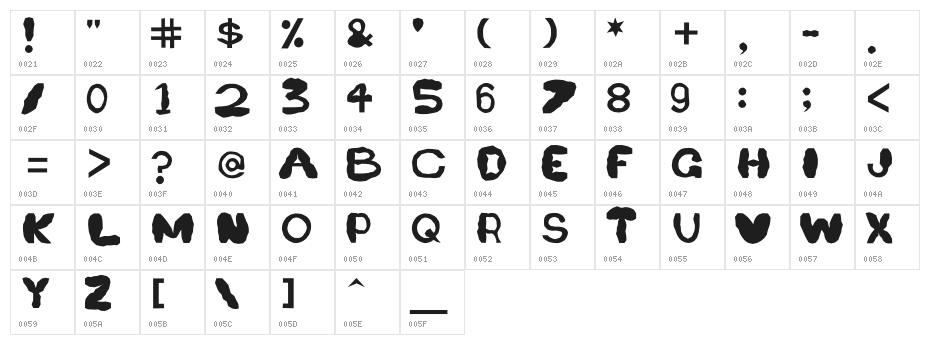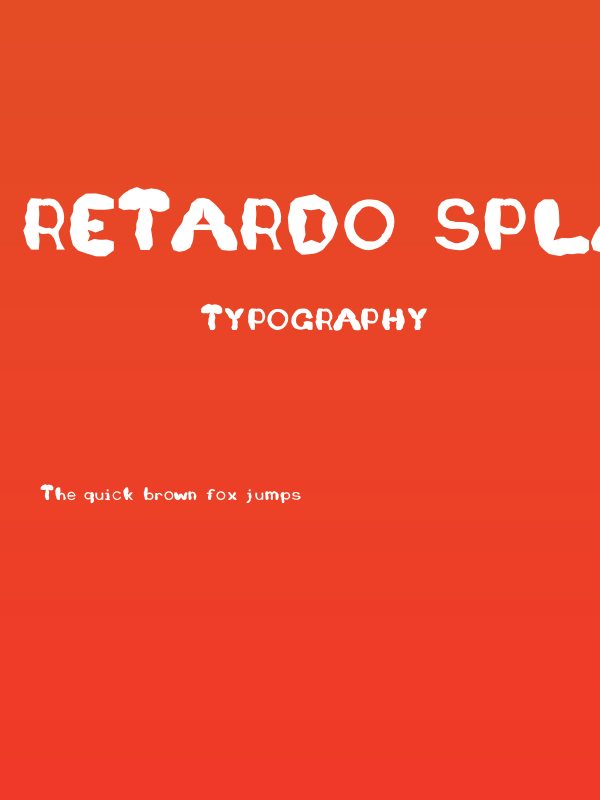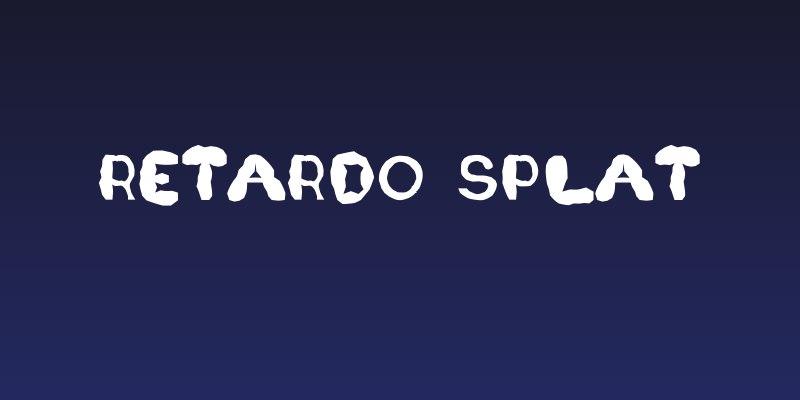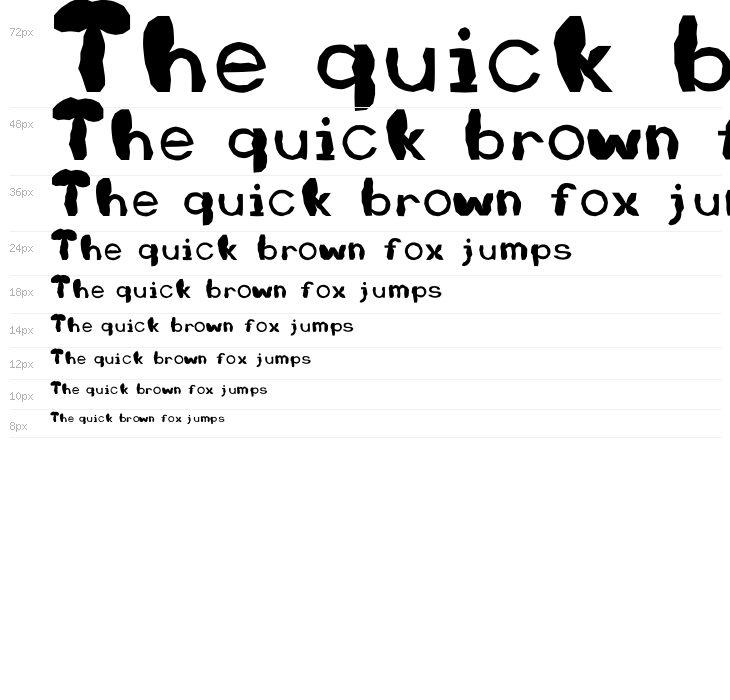
Retardo Splat Font
| Vorgeschlagene Projekte | Ideal for children's book covers, playful posters, creative branding, and artistic event invitations. |